Firefox 3.6 (!) oder Internet Explorer starten und auf das Bild oben klicken: Dann öffnet sich ein neues Fenster und Ihr könnt den aktuellen Test Webfont FF Nuvo Medium Web live in verschiedenen Größen auf eurem Bildschirm sehen und das Rendering begutachten. Bitte beachtet dabei, das FF Nuvo Medium – typografisch gesehen – keine Schrift ist, die man dringend zum Darstellen längerer Texte empfehlen würde: Ihre Formen haben keine Antiqua-Architektur.
Web-FontFont: Der Livetest
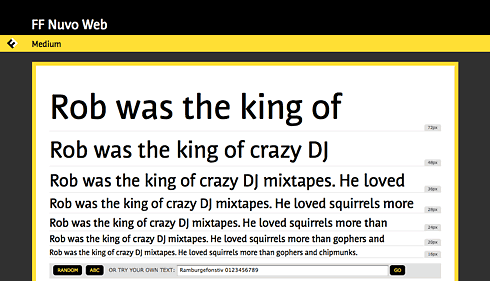
… keine Schrift ist, die man dringend zum Darstellen längerer Texte empfehlen würde …
Meiner Meinung nach ist der Bildschirm nach wie vor nicht das richtige Medium für längere Texte. Hier bevorzuge ich die gedruckte Form.
Trotzalledem: Schön, dass es funktioniert und es diese Möglichkeit endlich gibt!
Wenn Webkit-Browser mit WOFF-Support kommen (und Opera wird auch nachziehen), ist die Browserwelt nahezu “komplett”. Dafür, dass WOFF noch kein Jahr alt ist, beachtlich (und natürlich mit dem Glück erkauft, dass es EOT schon lange gibt – sonst würden wir warten bis zum St. Nimmerleinstag).
Aber: grade wenn ich die FF Nuvo ansehe, bin ich immer mehr davon überzeugt, dass eine Weblizenz-Version einer bisherigen Printschrift noch nicht automatisch eine Screen-Version wird, indem man sie in WOFF wandelt und ggf. das Hinting verbessert. Eventuell täte ihr auch eine Verbreiterung der Buchstabenformen und ggf. eine Lockerung der Metrik gut – viel Arbeit, sogar schon der Versuch, ob’s was nützt. (Headline-Anwendung natürlich mal ausgenommen – da geht vieles.)
In deiner Statistik schenkst du dir etwa 20 Prozentpunkte, indem du Firefox pauschal als unterstützt zählst. Wenn du bei der angegebenen Quelle aber weiter klickst, siehst du, dass größtenteils noch Firefox ≤ 3.5 im Einsatz ist. Das dürfte sich zugegebenermaßen aber in den nächsten Wochen ändern.
Ich nutze Safari (Standard) und Firefox parallel, WordPress (das Fontbloggen) unter Safari ist sehr unzuverlässig. Klar hab’ ich mich vor 4-6 Jahren stets geärgert, wenn ich eine Site besucht habe, die Safari nicht unterstützte, vor allem, als es noch kein Firefox gab. Diese Zeiten sind zum Glück vorbei. Bei den Webfonts unter Safari geht es ja »nur« um die Einschränkung, dass für eine ungewisse Zeit statt einer gewünschten Schrift die Ersatzschrift angezeigt wird. Die Funktionstüchtigkeit einer solchen Seite ist ansonsten kein bisschen gefährdet.
Also die FF Nuvo Web sieht doch erstaunlich gut unter WinXP (Firefox 3.6 + Cleartype) aus. Bis 14px kann man sie gut einsetzen.